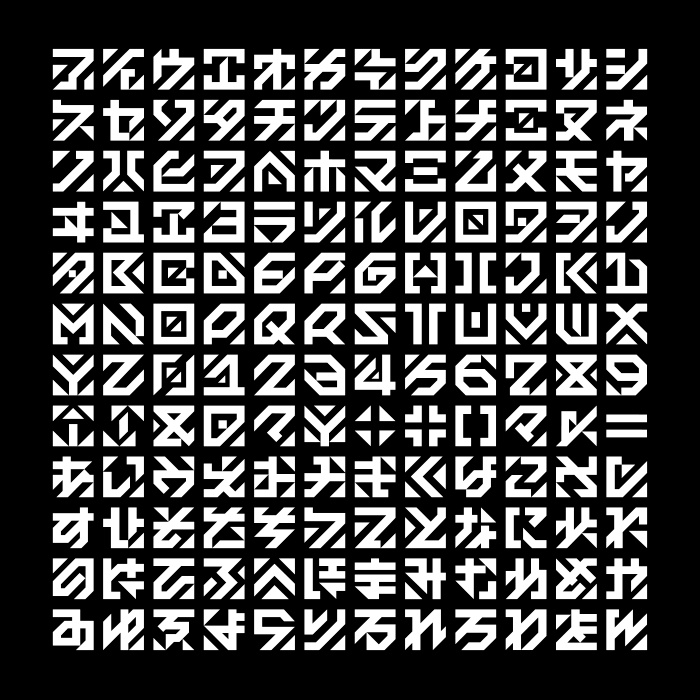
インビジブル フォント
フォント名:インビジブル(Invisibles)
読めないフォントを作りました。読めるか読めないかはあなた次第。ふとマンガの背景用にと作ってみました。漫画、ゲーム、動画にも使い方によっては面白く使えると思います。石板に書かれた古代文字のような、はたまた未来の文字なのか、あなたの自由なイメージで使ってください。
ひらがな、カタカナ、アルファベットのみの書体になります。